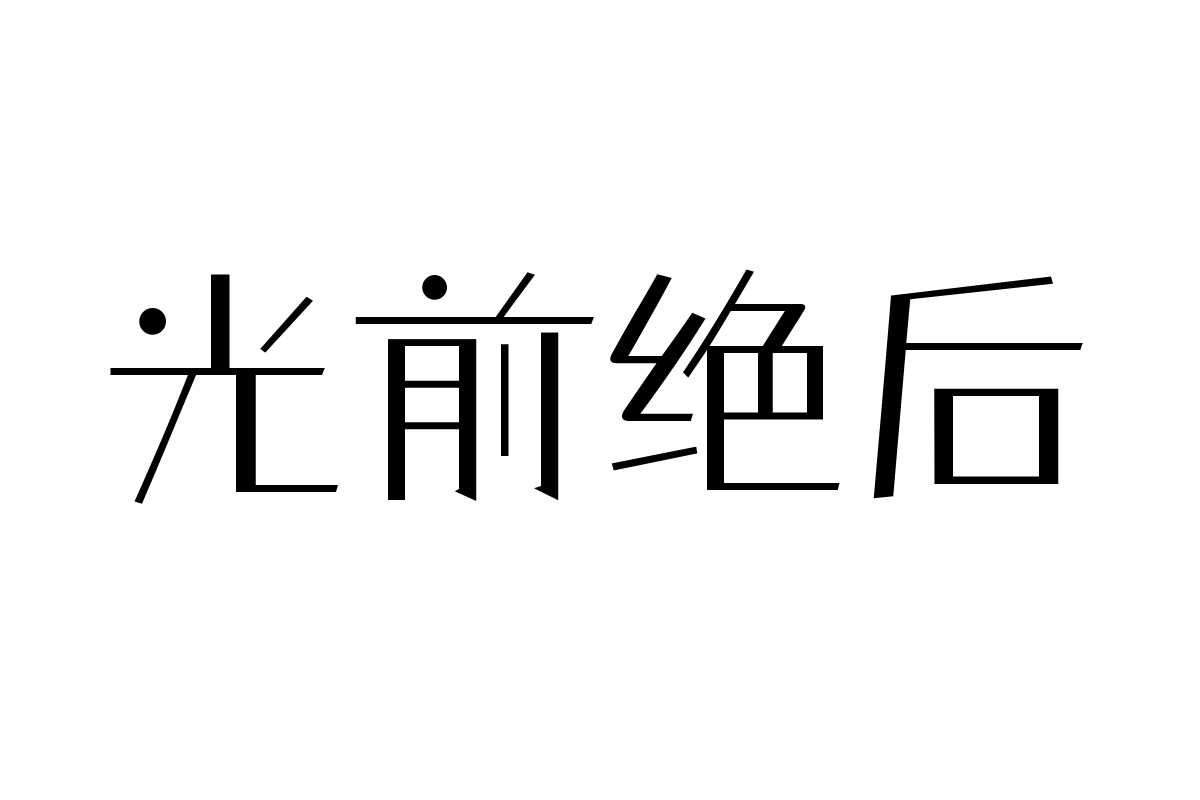
仓耳非白W02是一款**粗细对比明显、风格强烈,拥有5个字重的家族字体**。
仓耳非白W02的设计风格独特,它通过粗细分明的笔形和结构方正的字形,强调了“黑”与“白”的对比。这种设计不仅使得字体具有辨识度,也赋予了其强烈的视觉冲击力。在细节处理上,如字形转折处均做直角处理,进一步突出了字体的现代感和简约风。